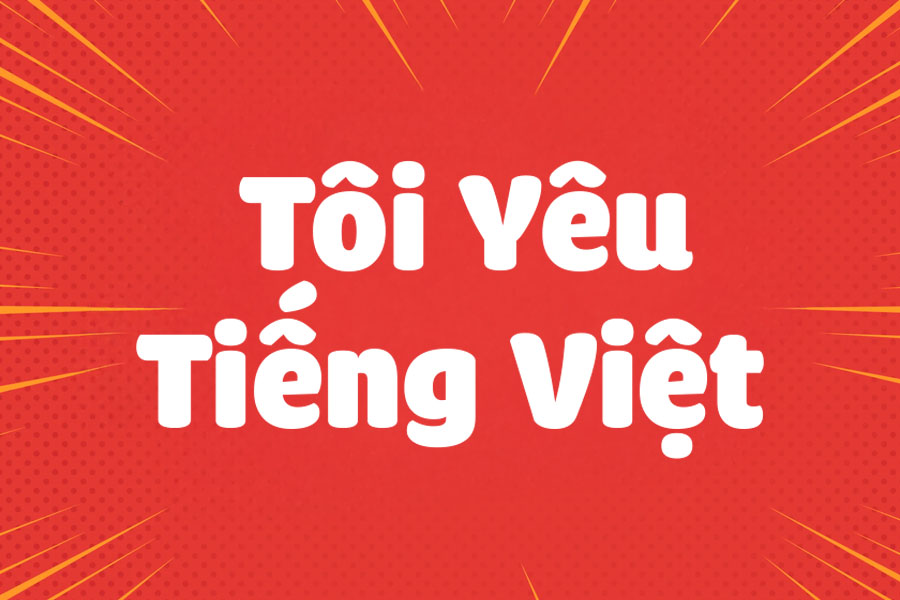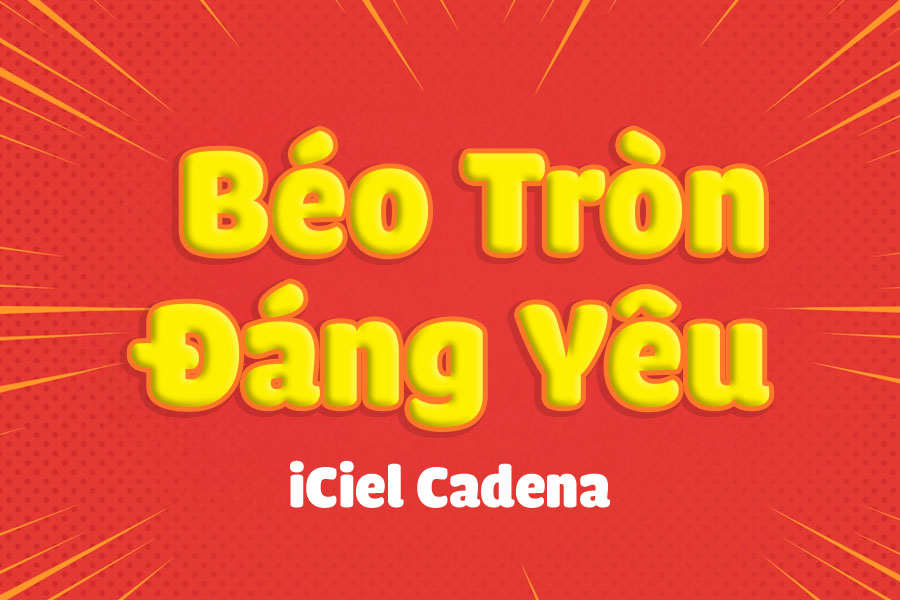
Trong thế giới thiết kế sáng tạo, những font chữ tròn trịa và vui nhộn luôn có sức hút đặc biệt, mang lại cảm giác gần gũi và thân thiện. Một trong những lựa chọn tiêu biểu chính là font iCiel Cadena, phiên bản Việt hóa của bộ font Cadena nổi tiếng. Font chữ này được sáng tạo bởi Harold’s Fonts, sau đó được iCiel Team Việt hóa, giúp người dùng tại Việt Nam có thể sử dụng đầy đủ dấu tiếng Việt một cách mượt mà, tiện lợi.
Điểm nổi bật nhất của iCiel Cadena nằm ở cấu trúc chữ béo tròn, bo góc mềm mại và dày dặn. Mỗi ký tự đều mang dáng vẻ đáng yêu, dễ thương, gợi liên tưởng đến những viên kẹo ngọt ngào hoặc các thiết kế dành riêng cho trẻ em. Chính sự mềm mại và cân đối trong từng chi tiết đã giúp iCiel Cadena trở thành một font chữ display nổi bật, dễ dàng thu hút ánh nhìn ngay từ lần đầu tiên.
Về ứng dụng, font iCiel Cadena đặc biệt phù hợp trong các thiết kế poster, bao bì sản phẩm, logo, banner quảng cáo, thiệp chúc mừng hay các dự án sáng tạo mang màu sắc vui nhộn. Với tinh thần tươi vui và năng động, font này thường được các nhà thiết kế lựa chọn cho những sản phẩm hướng đến trẻ em, đồ ăn vặt, đồ uống hoặc các thương hiệu cần yếu tố đáng yêu để tạo ấn tượng.
Phiên bản Việt hóa bởi iCiel đã giữ nguyên phong cách đặc trưng của bản gốc nhưng đồng thời tối ưu để hỗ trợ tiếng Việt đầy đủ, mang lại sự tiện lợi và linh hoạt cho các nhà thiết kế trong nước. Đây chính là điểm cộng lớn khiến iCiel Cadena được ưa chuộng, không chỉ bởi vẻ đẹp thẩm mỹ mà còn bởi tính ứng dụng thực tiễn.
Với phong cách vui nhộn, đáng yêu và hiện đại, iCiel Cadena chắc chắn sẽ là lựa chọn hoàn hảo cho những ai muốn mang đến diện mạo độc đáo, sáng tạo và dễ nhớ cho các dự án thiết kế của mình.
Font chữ iCiel Cadena – Đáng yêu, vui nhộn và tràn đầy sức sống